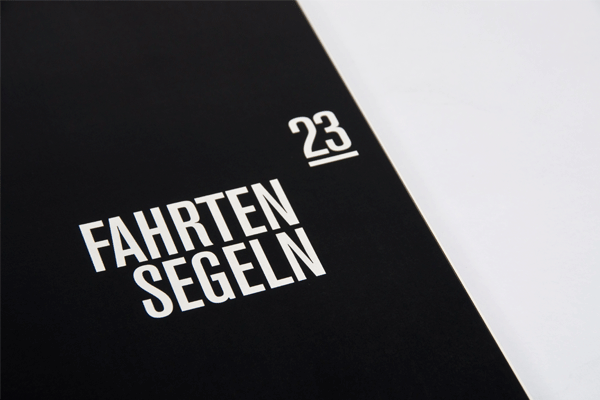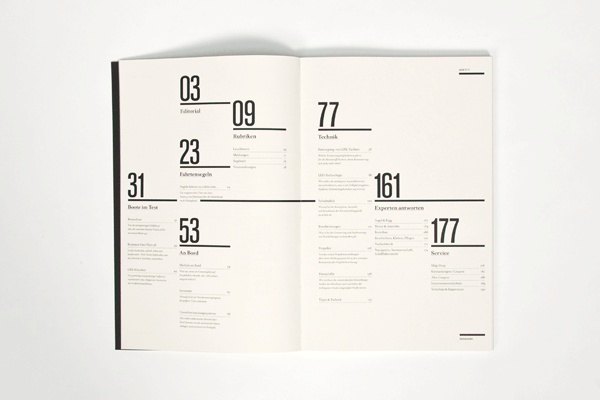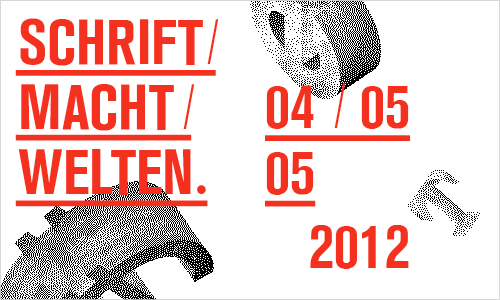
wichtig! welche schrift ist das bloß ?
Ich bin auf der Suche nach dieser Schrift!
Kann mir jemand weiterhelfen?
Das sind verschiedene … "Schrift macht Welten" sieht nach Akzidenz Grotesk aus, aber das R passt nicht.
Beim Segeln passt das S nicht ganz … aber vielleicht täusch ich mich auch.